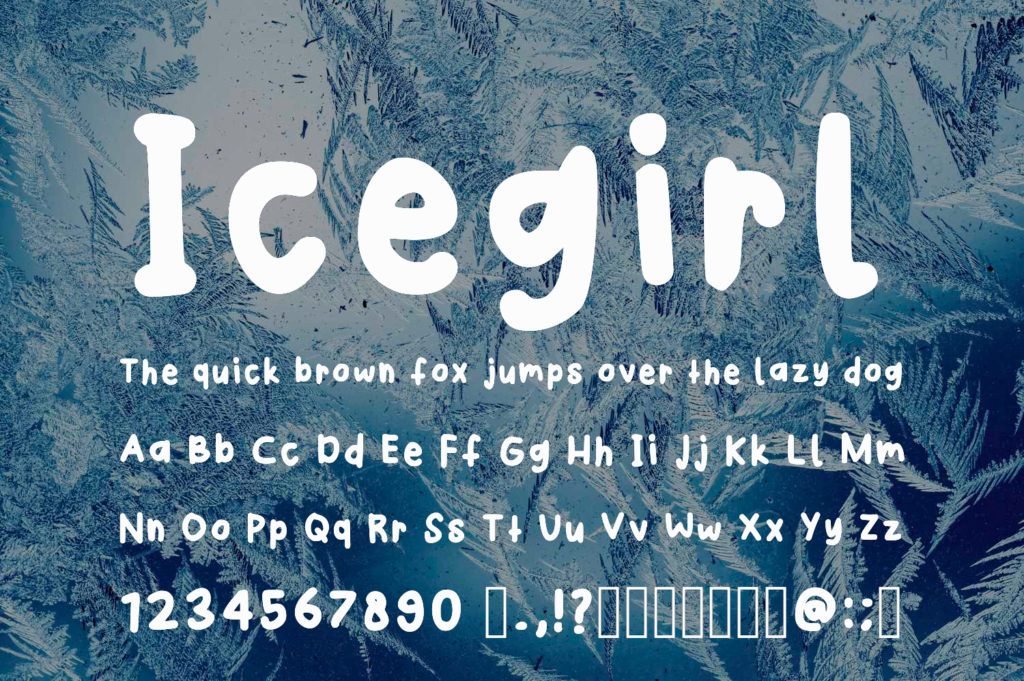
это игривый рукописный шрифт в стиле комикс от студии Salstudiees (автор Salsabila Shabriyyah), выпущенный в 2021 году. Изначально разработанный для латинского алфавита, он отличается плавными линиями и «ледяным», женственным характером. Адаптированная кириллическая версия сохраняет оригинальную легкость и воздушность начертания. Этот шрифт отлично подходит для создания нежного, личного настроения в дизайне. Вы можете скачать бесплатно кириллическую версию Ice Girl на нашем сайте и использовать её в личных проектах